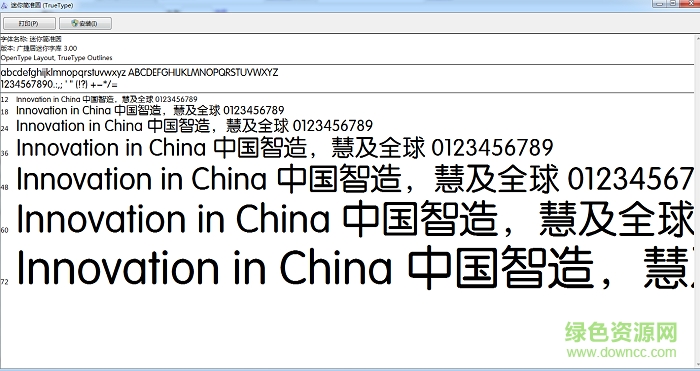
jzun yuan字體又叫迷你簡(jiǎn)準(zhǔn)圓,是一款適合用于廣告、影視、雜志、包裝設(shè)計(jì)等各種領(lǐng)域的圓體字體,外形圓潤(rùn)辨識(shí)度高,一般在平面廣告詞上都是比較常見(jiàn)的,也非常的實(shí)用,綠色資源網(wǎng)還有豐富的漂亮字體等你下載!
國(guó)內(nèi)所謂的圓體字形似Copperplate,但沒(méi)有粗細(xì)變化和華麗的修飾。其變體為幼圓體、琥珀體等